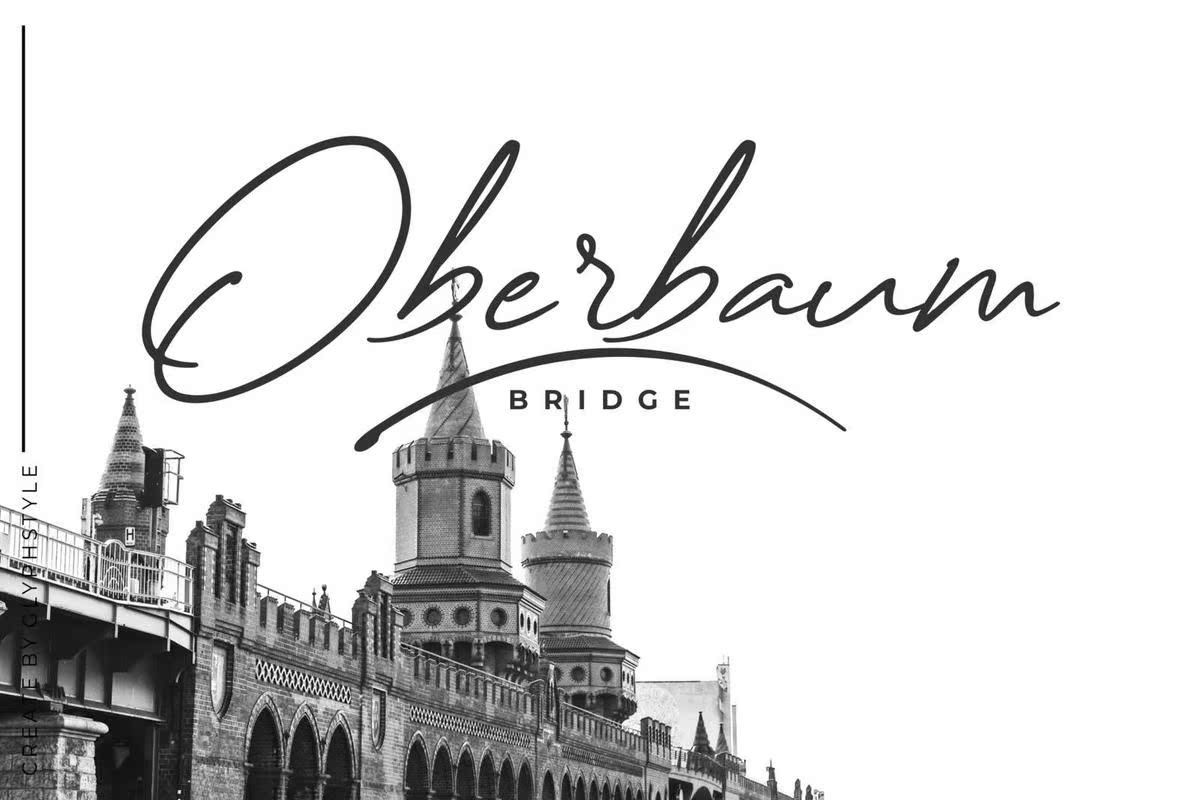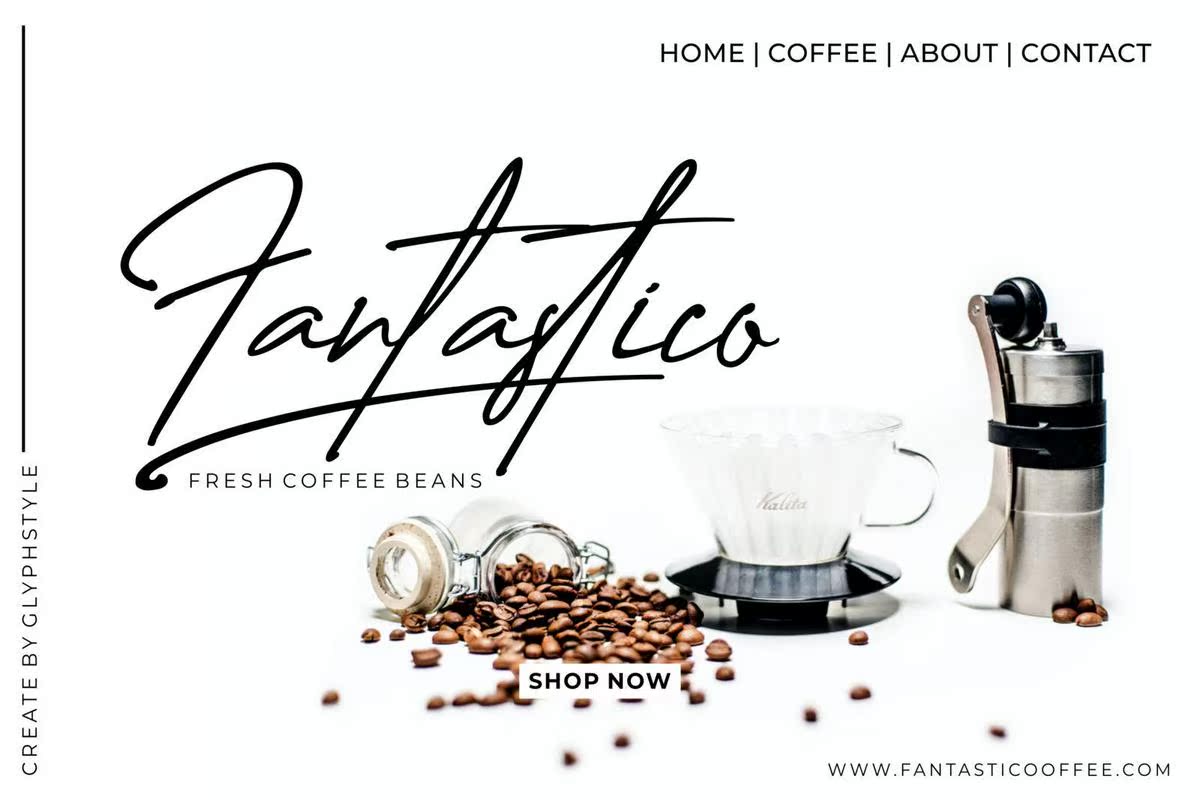
创意是一款具有独特风格和墨水效果的签名。优雅、丰富的自然和绘画风格。此签名适用于婚礼、水印、品牌,如采访、名片、产品徽标等。创意适用于品牌项目、徽标、婚礼设计、社交媒体、广告、产品包装、产品设计、标签、摄影、,水印、邀请函、文具和任何需要对签名和风格感兴趣的项目。创意是一种具有自然风格和墨水效果的设计。优雅而丰富的自然和绘画风格。该设计适用于婚礼、水印、品牌推广,如采访、名片、产品徽标等。创意适用于品牌项目、徽标、,婚礼设计、社交媒体、广告、产品包装、产品设计、标签、摄影、水印、邀请函、文具以及任何需要签名和风格感的项目。